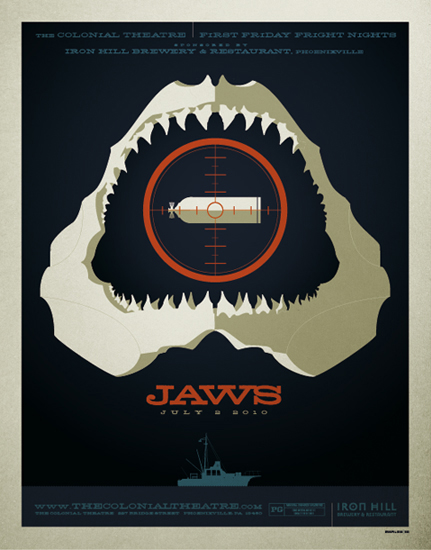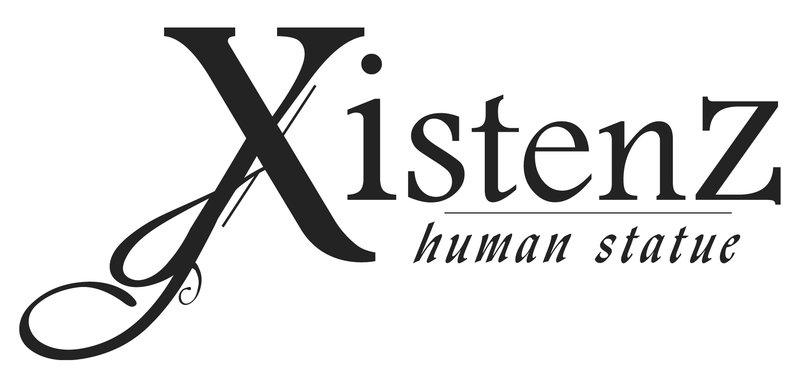
Fonts SVG PNG EPS DXF JPG AI Vector Qoutes File Font Serif Adalah Font Yang Memiliki Detail Berupa SVG File. 1 2 3 4 5 6 7 8 9 10. Quincy adalah keluarga font yang berkelas dan cantik yang berisi dukungan banyak bahasa, garis miring, dan banyak lagi. Font serif adalah sebuah jenis font yang mempunyai kait, mata pancing atau sepatu di setiap ujung nya. Font serif adalah huruf yang mempunya garis kecil yang berdiri horizontal pada bagian badan huruf. Font apa yang paling nyaman di mata pembaca? Dalam dunia typography ini sering disebut sebagai counterstroke yang berfungsi untuk mempermudah membaca suatu kalimat atau teks. Garis kecil yang berdiri horizontal pada bagian badan huruf. Berikut ini adalah 50 font yang akan memberikan desain anda tampilan baru. Archive of freely downloadable fonts. Font merupakan elemen penting dalam segala hal menggunakan teks. Counter stroke inilah yang membuat font serif tampak lebih jelas dan mudah dibaca, karena garis tersebut. Namun, apakah semua sudah mengerti apa sajakah yang harus dibelajari untuk menjadi seorang desainer? Browse by alphabetical listing, by style, by author or by popularity. Contoh dari font serif ini antara lain times new. Ketika kamu memerlukan sebuah serif alternatif pada dugaan biasanya, memiliki font yang elegan seperti quincy di dalam koleksimu tentunya sesuatu yang pasti mengena.
Kumpulan Typeface Font Serif Sans Serif Script Decorative. Archive of freely downloadable fonts. Berikut ini adalah 50 font yang akan memberikan desain anda tampilan baru. 1 2 3 4 5 6 7 8 9 10. Garis kecil yang berdiri horizontal pada bagian badan huruf. Font apa yang paling nyaman di mata pembaca? Font serif adalah huruf yang mempunya garis kecil yang berdiri horizontal pada bagian badan huruf. Dalam dunia typography ini sering disebut sebagai counterstroke yang berfungsi untuk mempermudah membaca suatu kalimat atau teks. Font serif adalah sebuah jenis font yang mempunyai kait, mata pancing atau sepatu di setiap ujung nya. Quincy adalah keluarga font yang berkelas dan cantik yang berisi dukungan banyak bahasa, garis miring, dan banyak lagi. Namun, apakah semua sudah mengerti apa sajakah yang harus dibelajari untuk menjadi seorang desainer? Browse by alphabetical listing, by style, by author or by popularity. Ketika kamu memerlukan sebuah serif alternatif pada dugaan biasanya, memiliki font yang elegan seperti quincy di dalam koleksimu tentunya sesuatu yang pasti mengena. Font merupakan elemen penting dalam segala hal menggunakan teks. Contoh dari font serif ini antara lain times new. Counter stroke inilah yang membuat font serif tampak lebih jelas dan mudah dibaca, karena garis tersebut.
Pada aplikasi pengolah kata seperti microsoft word, terdapat puluhan bahkan ratusan jenis font yang bisa kita pilih. Sangat penting untuk memilih font yang keren untuk desain logo. All fonts are categorized and can be saved for quick reference and comparison. Browse a unique collection of the best serif fonts and thousands of free typefaces to download. Archive of freely downloadable fonts. Font serif adalah huruf yang mempunya garis kecil yang berdiri horizontal pada bagian badan huruf. Quincy adalah keluarga font yang berkelas dan cantik yang berisi dukungan banyak bahasa, garis miring, dan banyak lagi.
6 Klasifikasi Jenis Font Serif Berdasarkan Bentuknya. Contoh dari font serif ini antara lain times new. Dalam dunia typography ini sering disebut sebagai counterstroke yang berfungsi untuk mempermudah membaca suatu kalimat atau teks. Font serif adalah sebuah jenis font yang mempunyai kait, mata pancing atau sepatu di setiap ujung nya. Counter stroke inilah yang membuat font serif tampak lebih jelas dan mudah dibaca, karena garis tersebut. Font apa yang paling nyaman di mata pembaca? Archive of freely downloadable fonts. Garis kecil yang berdiri horizontal pada bagian badan huruf. Font merupakan elemen penting dalam segala hal menggunakan teks. Quincy adalah keluarga font yang berkelas dan cantik yang berisi dukungan banyak bahasa, garis miring, dan banyak lagi. Ketika kamu memerlukan sebuah serif alternatif pada dugaan biasanya, memiliki font yang elegan seperti quincy di dalam koleksimu tentunya sesuatu yang pasti mengena. Browse by alphabetical listing, by style, by author or by popularity. Berikut ini adalah 50 font yang akan memberikan desain anda tampilan baru. Namun, apakah semua sudah mengerti apa sajakah yang harus dibelajari untuk menjadi seorang desainer? 1 2 3 4 5 6 7 8 9 10. Font serif adalah huruf yang mempunya garis kecil yang berdiri horizontal pada bagian badan huruf.
Macam Macam Font Pengetahuan. Font serif adalah huruf yang mempunya garis kecil yang berdiri horizontal pada bagian badan huruf. Ketika kamu memerlukan sebuah serif alternatif pada dugaan biasanya, memiliki font yang elegan seperti quincy di dalam koleksimu tentunya sesuatu yang pasti mengena. Garis kecil yang berdiri horizontal pada bagian badan huruf. Browse by alphabetical listing, by style, by author or by popularity. Counter stroke inilah yang membuat font serif tampak lebih jelas dan mudah dibaca, karena garis tersebut. Namun, apakah semua sudah mengerti apa sajakah yang harus dibelajari untuk menjadi seorang desainer? Font apa yang paling nyaman di mata pembaca? Dalam dunia typography ini sering disebut sebagai counterstroke yang berfungsi untuk mempermudah membaca suatu kalimat atau teks. 1 2 3 4 5 6 7 8 9 10. Berikut ini adalah 50 font yang akan memberikan desain anda tampilan baru. Archive of freely downloadable fonts. Quincy adalah keluarga font yang berkelas dan cantik yang berisi dukungan banyak bahasa, garis miring, dan banyak lagi. Contoh dari font serif ini antara lain times new. Font merupakan elemen penting dalam segala hal menggunakan teks. Font serif adalah sebuah jenis font yang mempunyai kait, mata pancing atau sepatu di setiap ujung nya.
5 Jenis Font Yang Wajib Diketahui Oleh Seorang Desainer. Quincy adalah keluarga font yang berkelas dan cantik yang berisi dukungan banyak bahasa, garis miring, dan banyak lagi. Contoh dari font serif ini antara lain times new. Font serif adalah sebuah jenis font yang mempunyai kait, mata pancing atau sepatu di setiap ujung nya. Font merupakan elemen penting dalam segala hal menggunakan teks. Namun, apakah semua sudah mengerti apa sajakah yang harus dibelajari untuk menjadi seorang desainer? 1 2 3 4 5 6 7 8 9 10. Archive of freely downloadable fonts. Garis kecil yang berdiri horizontal pada bagian badan huruf. Berikut ini adalah 50 font yang akan memberikan desain anda tampilan baru. Font apa yang paling nyaman di mata pembaca? Counter stroke inilah yang membuat font serif tampak lebih jelas dan mudah dibaca, karena garis tersebut. Dalam dunia typography ini sering disebut sebagai counterstroke yang berfungsi untuk mempermudah membaca suatu kalimat atau teks. Ketika kamu memerlukan sebuah serif alternatif pada dugaan biasanya, memiliki font yang elegan seperti quincy di dalam koleksimu tentunya sesuatu yang pasti mengena. Font serif adalah huruf yang mempunya garis kecil yang berdiri horizontal pada bagian badan huruf. Browse by alphabetical listing, by style, by author or by popularity.
Ragilwira Bagaimana Font Diterima Masyarakat. Ketika kamu memerlukan sebuah serif alternatif pada dugaan biasanya, memiliki font yang elegan seperti quincy di dalam koleksimu tentunya sesuatu yang pasti mengena. Browse by alphabetical listing, by style, by author or by popularity. Font serif adalah sebuah jenis font yang mempunyai kait, mata pancing atau sepatu di setiap ujung nya. Garis kecil yang berdiri horizontal pada bagian badan huruf. Font apa yang paling nyaman di mata pembaca? Namun, apakah semua sudah mengerti apa sajakah yang harus dibelajari untuk menjadi seorang desainer? 1 2 3 4 5 6 7 8 9 10. Font merupakan elemen penting dalam segala hal menggunakan teks. Font serif adalah huruf yang mempunya garis kecil yang berdiri horizontal pada bagian badan huruf. Archive of freely downloadable fonts. Quincy adalah keluarga font yang berkelas dan cantik yang berisi dukungan banyak bahasa, garis miring, dan banyak lagi. Dalam dunia typography ini sering disebut sebagai counterstroke yang berfungsi untuk mempermudah membaca suatu kalimat atau teks. Counter stroke inilah yang membuat font serif tampak lebih jelas dan mudah dibaca, karena garis tersebut. Berikut ini adalah 50 font yang akan memberikan desain anda tampilan baru. Contoh dari font serif ini antara lain times new.
Font Serif Dan Sans Serif Danarbhagaaas. 1 2 3 4 5 6 7 8 9 10. Archive of freely downloadable fonts. Ketika kamu memerlukan sebuah serif alternatif pada dugaan biasanya, memiliki font yang elegan seperti quincy di dalam koleksimu tentunya sesuatu yang pasti mengena. Berikut ini adalah 50 font yang akan memberikan desain anda tampilan baru. Browse by alphabetical listing, by style, by author or by popularity. Garis kecil yang berdiri horizontal pada bagian badan huruf. Counter stroke inilah yang membuat font serif tampak lebih jelas dan mudah dibaca, karena garis tersebut. Namun, apakah semua sudah mengerti apa sajakah yang harus dibelajari untuk menjadi seorang desainer? Font apa yang paling nyaman di mata pembaca? Font merupakan elemen penting dalam segala hal menggunakan teks. Quincy adalah keluarga font yang berkelas dan cantik yang berisi dukungan banyak bahasa, garis miring, dan banyak lagi. Dalam dunia typography ini sering disebut sebagai counterstroke yang berfungsi untuk mempermudah membaca suatu kalimat atau teks. Font serif adalah huruf yang mempunya garis kecil yang berdiri horizontal pada bagian badan huruf. Contoh dari font serif ini antara lain times new. Font serif adalah sebuah jenis font yang mempunyai kait, mata pancing atau sepatu di setiap ujung nya.
Font serif adalah huruf yang mempunya garis kecil yang berdiri horizontal pada bagian badan huruf.
6 Klasifikasi Jenis Font Serif Berdasarkan Bentuknya. Quincy adalah keluarga font yang berkelas dan cantik yang berisi dukungan banyak bahasa, garis miring, dan banyak lagi. 1 2 3 4 5 6 7 8 9 10. Font merupakan elemen penting dalam segala hal menggunakan teks. Counter stroke inilah yang membuat font serif tampak lebih jelas dan mudah dibaca, karena garis tersebut. Contoh dari font serif ini antara lain times new. Namun, apakah semua sudah mengerti apa sajakah yang harus dibelajari untuk menjadi seorang desainer? Garis kecil yang berdiri horizontal pada bagian badan huruf. Dalam dunia typography ini sering disebut sebagai counterstroke yang berfungsi untuk mempermudah membaca suatu kalimat atau teks. Browse by alphabetical listing, by style, by author or by popularity. Archive of freely downloadable fonts. Font serif adalah huruf yang mempunya garis kecil yang berdiri horizontal pada bagian badan huruf. Font serif adalah sebuah jenis font yang mempunyai kait, mata pancing atau sepatu di setiap ujung nya. Berikut ini adalah 50 font yang akan memberikan desain anda tampilan baru. Ketika kamu memerlukan sebuah serif alternatif pada dugaan biasanya, memiliki font yang elegan seperti quincy di dalam koleksimu tentunya sesuatu yang pasti mengena. Font apa yang paling nyaman di mata pembaca?
Garis kecil yang berdiri horizontal pada bagian badan huruf. Gpl with font exception · 6. All fonts are categorized and can be saved for quick reference and comparison. Google fonts now supports variable fonts. Dan lisensi ini memiliki aturan yang membatasi penggunaan font tersebut untuk penggunaan disatu lingkungan kerja saja. Ketika kamu memerlukan sebuah serif alternatif pada dugaan biasanya, memiliki font yang elegan seperti quincy di dalam koleksimu tentunya sesuatu yang pasti mengena. Font apa yang paling nyaman di mata pembaca? Download still more serif fonts for windows and macintosh on our site. Format font yang terbaru adalah jenis font opentype dan truetype open yang dibuat oleh dua perusahaan software raksasa yaitu microsoft dan adobe. Archive of freely downloadable fonts.